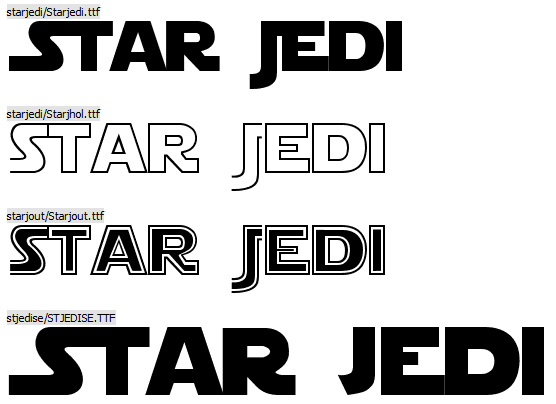
Aquí te dejo una colección de fuentes de películas famosas para que te descargues gratis. Cuanto representan algunas películas en nuestra vida. Es curioso como conseguimos identificar la tipografía con la película. No es lo mismo ver Superman escrito en una tipografía común tipo Arial o Verdana que en su tipografía original. Una buena selección de fuentes es síntoma de un buen diseño, y lo mismo se puede aplicar a las películas. El título de una película con una fuente adecuada ayuda a transmitir el mensaje de la película. Al descargarte la fuente, es recomendable que compruebes los derechos de utilización para darle un uso correcto.
Para todos los amantes del cine os invito a ver esta colección de fuentes de películas famosas:
Tipografía de Star Wars
Star Jedi es una fuente que simula a la utilizada en la película de la Guerra de las Galaxias y es una magnífica fuente de Star Wars. Si necesitas letras de star wars para imprimir estás en el sitio adecuado. Como me gusta esta tipografía de Star Wars.